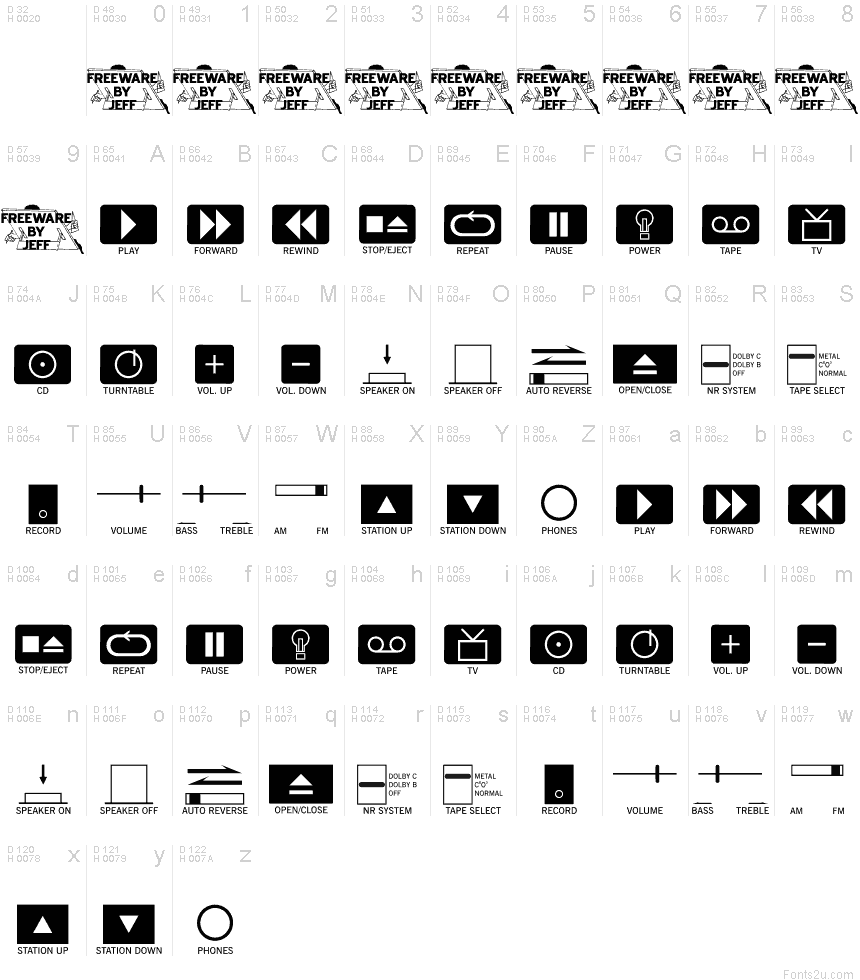
Buttons and Switches JL von Jeffrey N. Levine ist ein kostenloser Dingbat-Font, der den unverwechselbaren Look klassischer Mediensteuerungen einfängt. Jedes Symbol wirkt wie ein echter Button – Play, Pause, Zurückspulen, Wiederholen –, eingebettet in markante, schwarze Quadrate, die scharf, greifbar und sofort lesbar sind.
Buttons and Switches JL eignet sich hervorragend für Musikplayer, Podcast-Grafiken, Video-Overlays, Fernbedienungs-Mockups, Tech-Flyer, App-Prototypen und Retro-Electronics-Branding. Dieser kostenlose Font ist am besten in mittleren bis großen Größen lesbar; kombiniere ihn mit einer einfachen serifenlosen Schrift wie Helvetica oder Inter, damit die Icons scharf und vertraut wirken.
Suggested by the "King of Freeware Fonts", Ray Larabie. These dingbats are primarily buttons you'll find on CD players, cassette decks and VCR's.